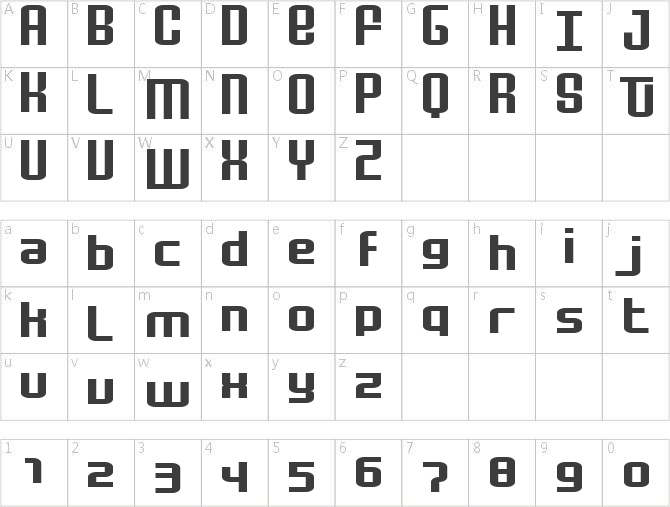
字体名称: Mocha-E
Mocha-Extended-Regular
Mocha-Extended-Regular介绍
Mocha-Extended-Regular字体字库是一款让人赏心悦目、百看不厌的英文字体,适合各类广告和产品包装设计应用,字体大小0.04MB,格式为ttf字体,上传用户是welking,作者/版权方为未知